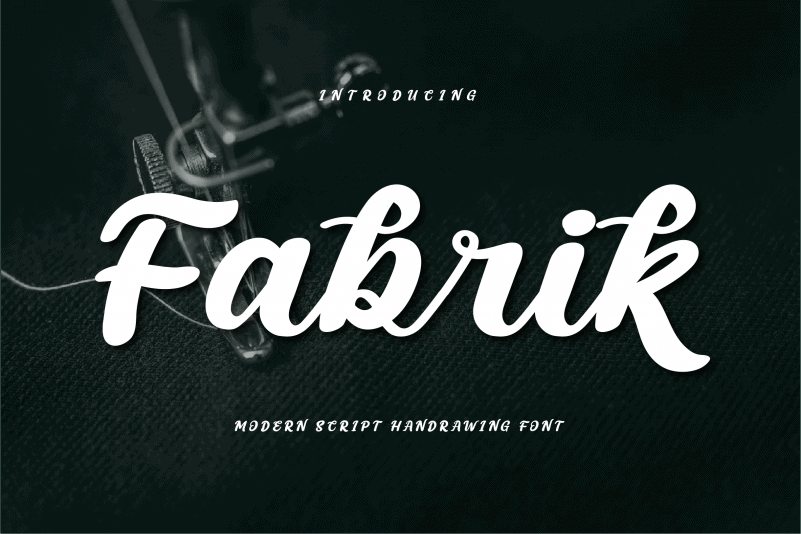
Fabrik Script Font – Download Grátis
A Fabrik Script Font é uma face tipográfica escrita à mão, meticulosamente criada para se tornar um verdadeiro preferido entre os designers e amantes do design. Ela preserva seus influentes traços de caligrafia enquanto mantém um toque contemporâneo e atual. Essa fonte é perfeita para quem busca uma abordagem elegante, combinando a sofisticação da caligrafia com a frescura da modernidade. Descubra seu encanto e transforme seus projetos em algo realmente único e de alto nível!